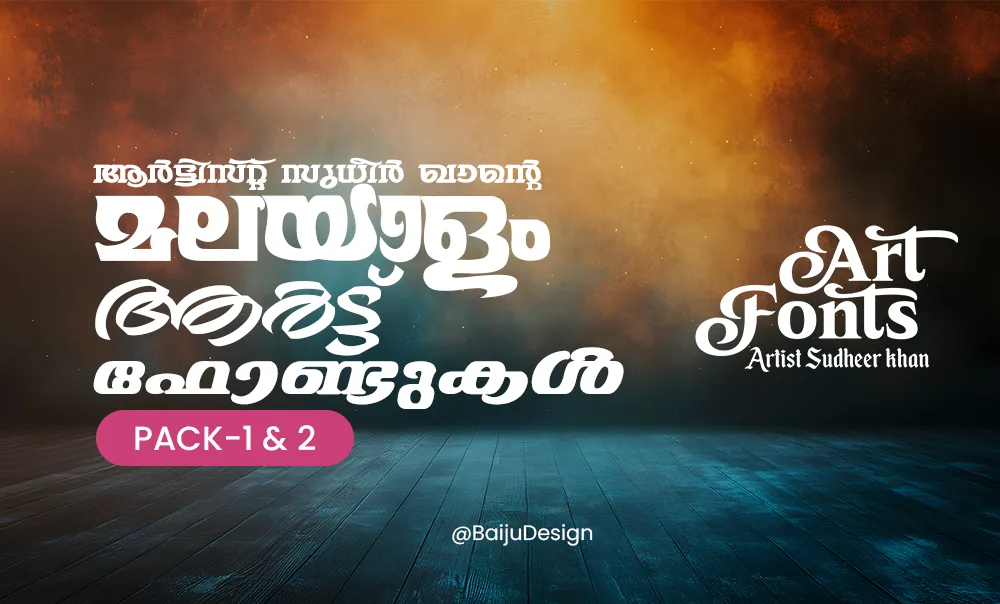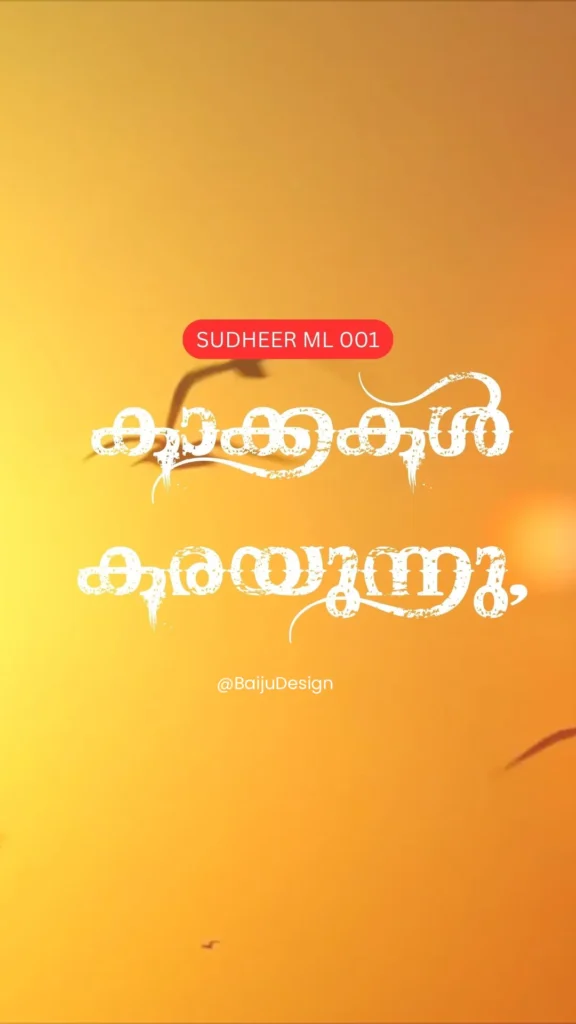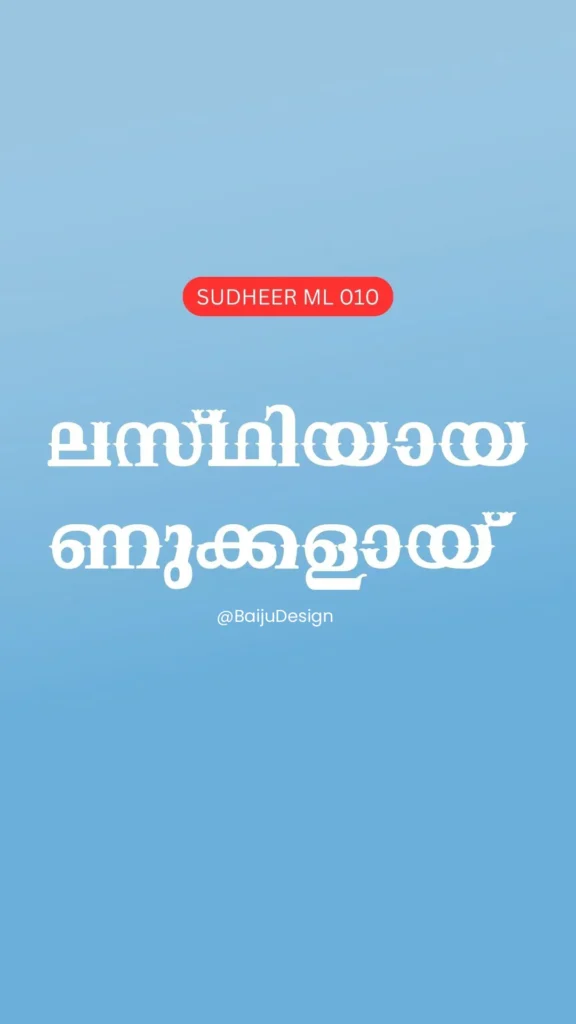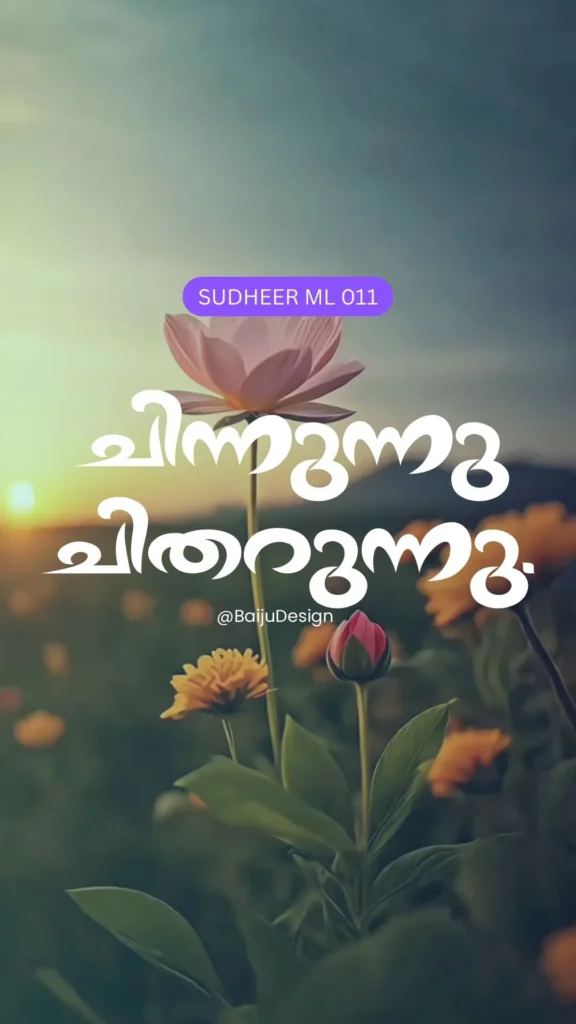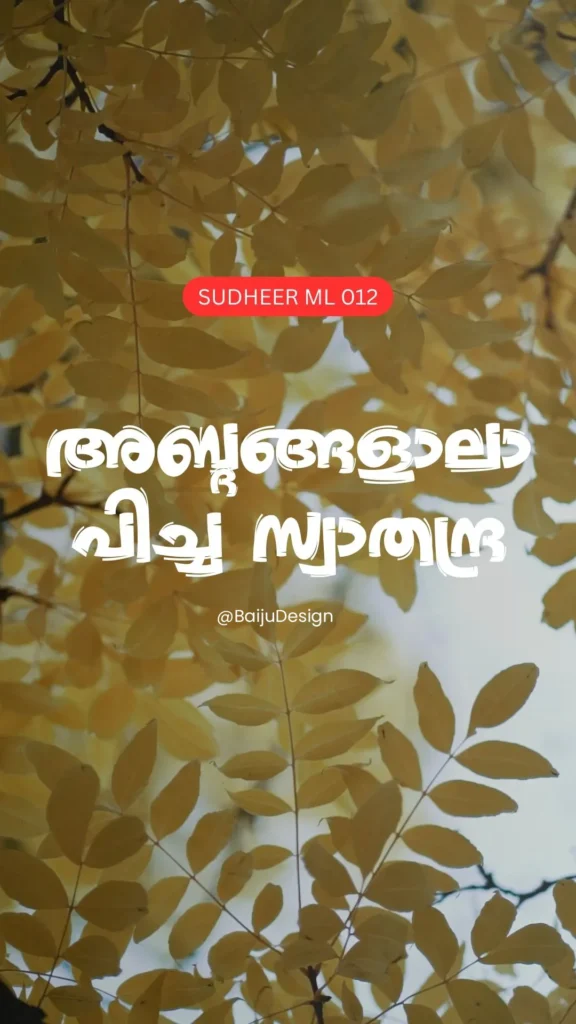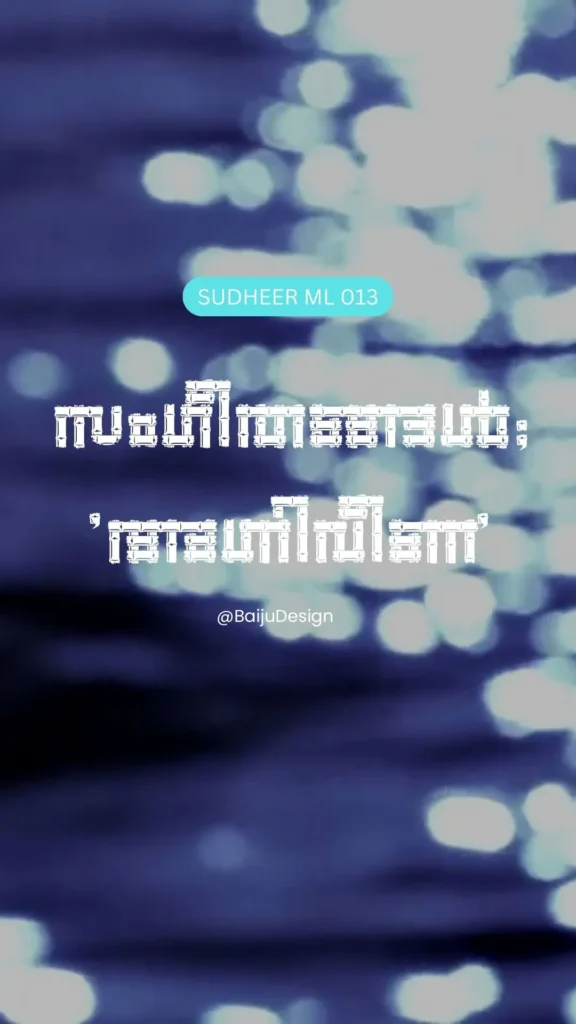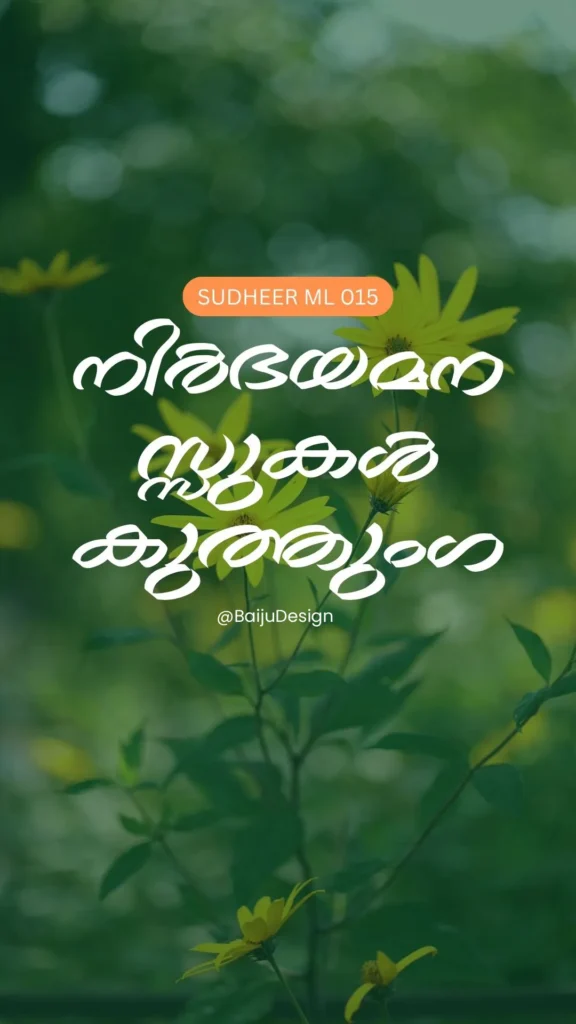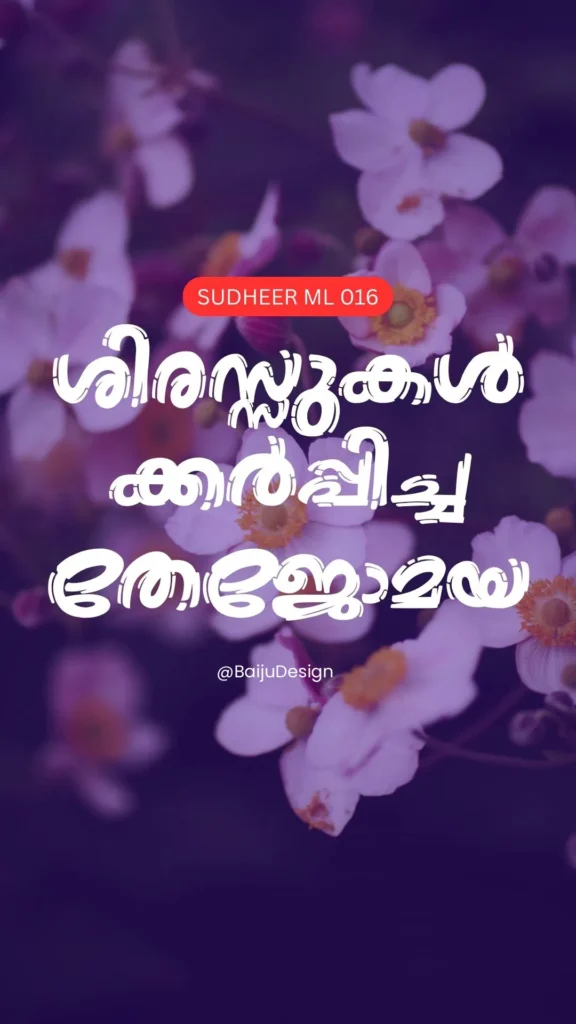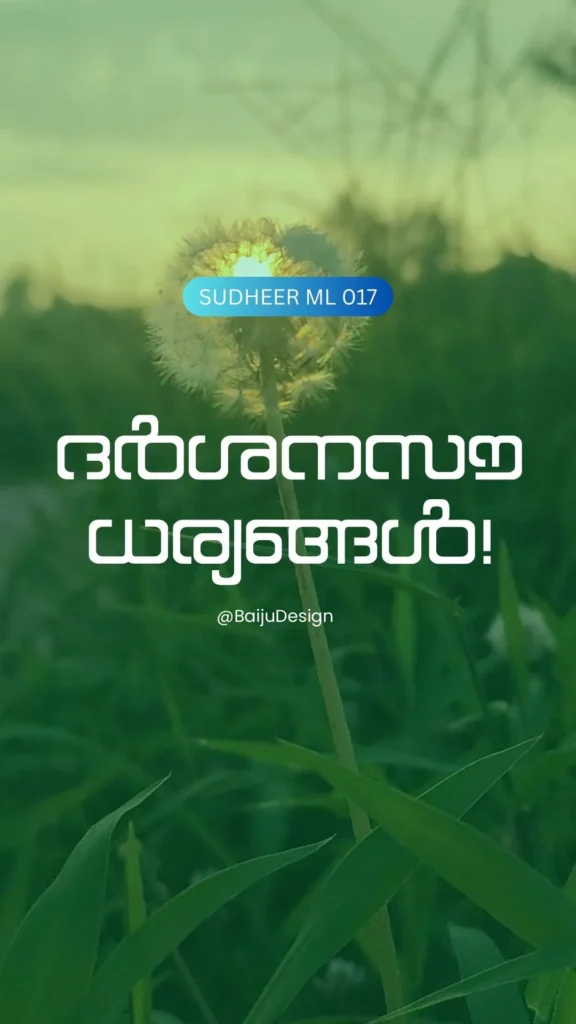
Malayalam Art Fonts | മലയാളത്തിന്റെ ആർട്ട് ഫോണ്ടുകൾ!
മലയാളത്തിന്റെ ഏറ്റവും വ്യത്യസ്തവും വലുതുമായ രണ്ടു ഫോണ്ട് പാക്കുകൾ ആണ് ആർട്ടിസ്റ്റ് സുധീർ ഖാന്റെ (Artist Sudheer Khan) ആർട്ട് ഫോണ്ടുകൾ.
ML ഫോണ്ട് സീരിസിൽ ഇറങ്ങിയിരിക്കുന്ന ഈ ഫോണ്ട് സെറ്റുകൾ നിങ്ങളുടെ ഡിസൈനുകൾ വളരെ ആകർഷകമുള്ളതാക്കാൻ സഹായിക്കുന്നു.
Font NameART FONTS SET (ആർട്ട് ഫോണ്ടുകൾ)
Language SupportMalayalam – ML- SERIES
Font TypeDecorative/Ornamental/Display/Headings
Creator / DesignerArtist Sudheer Khan
PublisherRenjith Chillezhuth/Artist Sudheer Khan
UsageBest for headings, body text, and branding